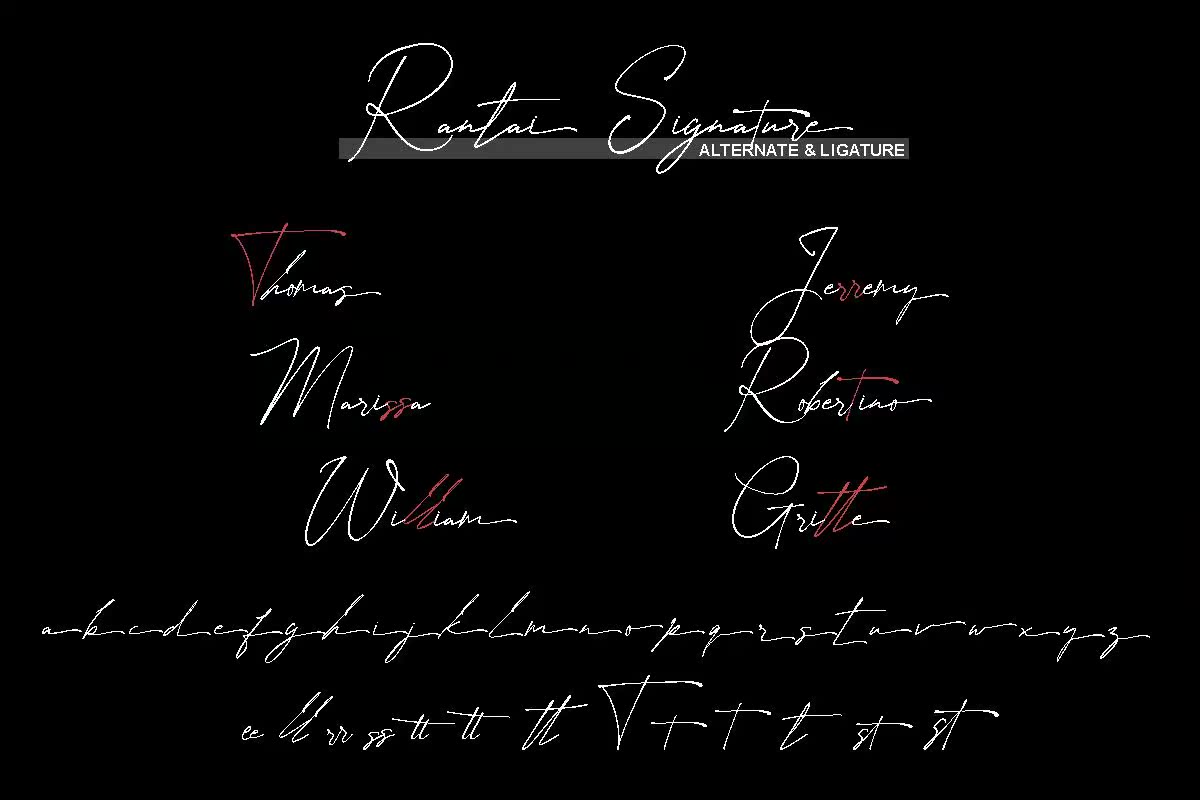
RANTAISIGNATION以全新和现代的笔划手写字体。此字体上添加了各种可选字符。此字体适用于徽标、时尚、文具、杂志、菜单、书籍、邀请函、问候卡、包装、标签、服装、营销、名片、,此字体上添加了各种可选字符。此字体适用于徽标、时尚、文具、杂志、菜单、书籍、邀请函、问候卡、包装、标签、服装、营销、名片等。